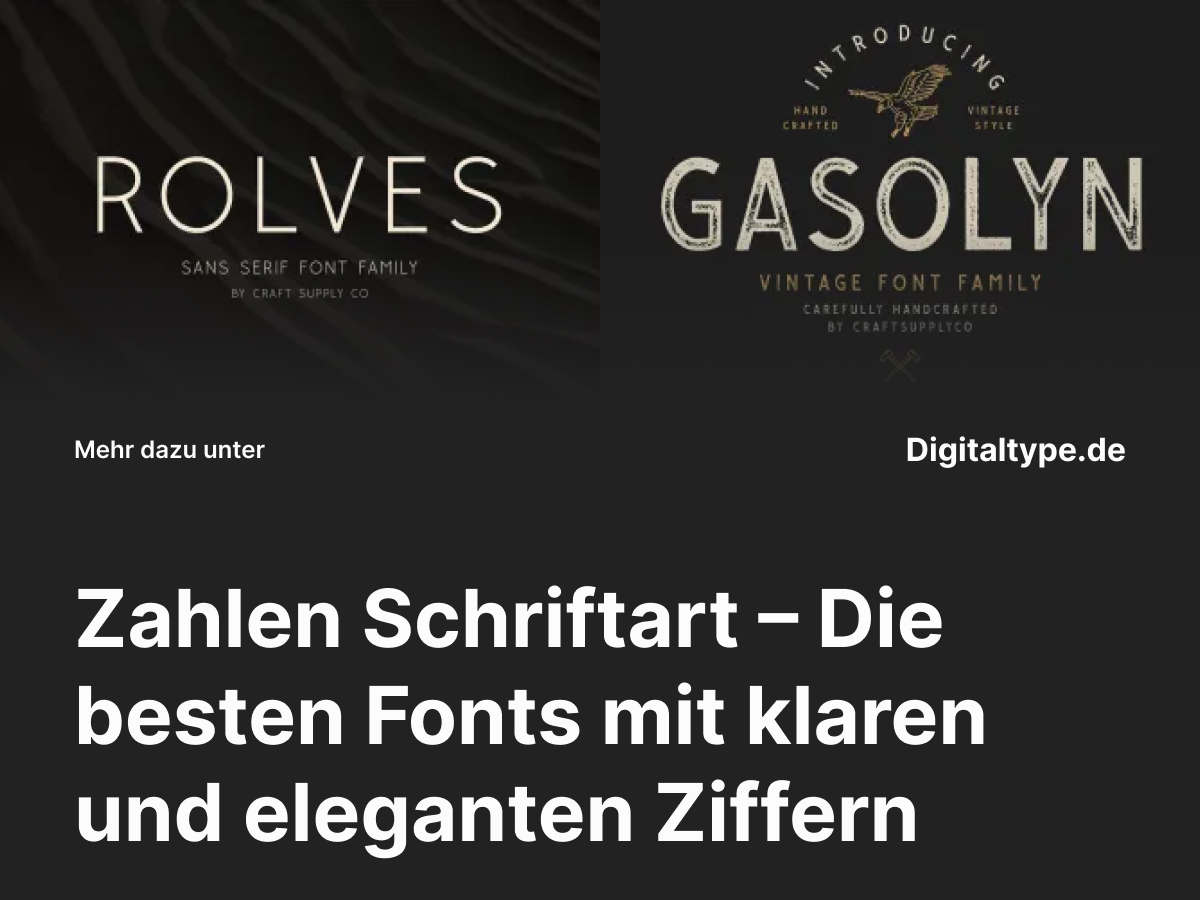
Ob für Preislisten, Infografiken oder Branding – eine gut gestaltete Zahlen Schriftart sorgt für Professionalität und visuelle Harmonie. Zahlen sind ein wesentlicher Bestandteil jedes Designs, und die richtige Schriftart kann sie zu einem echten Hingucker machen.
In diesem Artikel stellen wir dir stilvolle Schriftarten mit präzise gestalteten Ziffern vor, die sich ideal für moderne, elegante und vielseitige Anwendungen eignen.
Was ist eine Zahlen-Schriftart?
Unter einer Zahlen Schriftart versteht man einen Font, bei dem die Ziffern mit besonderem Augenmerk auf Lesbarkeit, Balance und Ästhetik gestaltet wurden. Sie spielt eine wichtige Rolle in Corporate Designs, Magazinen und digitalen Interfaces, wo klare und gleichmäßige Ziffern entscheidend sind.
Eine hochwertige Schriftart mit schönen Zahlen vermittelt Seriosität, Ordnung und Vertrauen – perfekt für Marken, die Wert auf jedes Detail legen.
Designer achten bei Zahlenfonts besonders auf konsistente Linienführung, Proportionen und Rhythmus. So entsteht ein harmonisches Gesamtbild, das Ziffern genauso ansprechend wirken lässt wie Buchstaben.
Wann du eine Zahlen-Schriftart verwenden solltest
- 1. Für Branding und Logos: Wenn dein Markenname oder Slogan Zahlen enthält (z. B. „Studio 89“ oder „Design 24“).
- 2. In Editorials und Magazinen: Für Seitenzahlen, Preisangaben oder Infoboxen mit elegantem Look.
- 3. Für Web- und UI-Designs: Damit Ziffern auf Bildschirmen klar, präzise und professionell wirken.
- 4. In luxuriösen oder technischen Layouts: Ideal für Marken, die Präzision, Qualität und Stil betonen möchten.
Die richtige Zahlen Schriftart sorgt dafür, dass Ziffern nicht nur funktional, sondern auch ästhetisch überzeugen – besonders in Projekten, bei denen Details zählen.
Die 6 besten Zahlen-Schriftarten für moderne Designs
Hier findest du sechs exklusive Zahlen Schriftarten, die durch Klarheit, Eleganz und typografische Qualität überzeugen. Perfekt für Branding, Print, Digital und kreative Designprojekte.
1. Rolves Sans Serif Font Family
Rolves ist eine moderne Sans-Serif-Schrift mit präzisen Ziffern und ausgewogener Geometrie. Ihre klaren Formen eignen sich ideal für Branding, Editorials und digitale Anwendungen, bei denen Lesbarkeit im Vordergrund steht.
2. Gasolyn Font Family + Extras
Gasolyn kombiniert moderne Typografie mit Vintage-Charme. Die Ziffern sind ausdrucksstark und perfekt proportioniert – ideal für kreative Projekte, Plakate und Packaging mit Charakter.
3. Coldiac Luxury Serif Font
Coldiac ist eine luxuriöse Serifenschrift mit fein ausgearbeiteten Zahlenformen. Sie verleiht jedem Design Eleganz und Raffinesse, besonders in Mode-, Schmuck- oder Premium-Branding-Projekten.
4. Riffle Font Family
Riffle bietet moderne Eleganz mit klassischer Struktur. Ihre klaren und gut ausbalancierten Ziffern sind ideal für Geschäftsberichte, Editorials und Corporate Designs, die Seriosität ausstrahlen.
5. Aguero Serif – Clean Elegant Font
Aguero überzeugt durch feine Linien und klare Geometrie. Die Ziffern wirken professionell und elegant zugleich – perfekt für Projekte, bei denen Präzision und Stil im Vordergrund stehen.
6. Espoir Serif Font Family
Espoir ist eine elegante Serifenschrift mit klassischer Note. Ihre sorgfältig gestalteten Ziffern passen perfekt zu edlen Layouts, Magazinen oder Corporate Designs im Premium-Segment.
Design-Tipps für Zahlen-Schriftarten
- 1. Achte auf Lesbarkeit: Besonders bei kleinen Größen oder digitalen Displays sollten Ziffern klar erkennbar bleiben.
- 2. Verwende proportionale Zahlen: Sie sorgen für ein gleichmäßiges Schriftbild im Fließtext.
- 3. Kombiniere Serif und Sans Serif: So entsteht ein dynamischer, moderner Look in deinen Layouts.
- 4. Teste verschiedene Schriftschnitte: Fettere Ziffern können in Überschriften stärker wirken als im Fließtext.
Fazit: Zahlen-Schriftarten für Stil und Präzision
Eine Zahlen Schriftart ist mehr als nur ein funktionales Detail – sie ist ein Ausdruck von Stil, Ordnung und Qualität. Die richtigen Ziffern verleihen deinem Design Eleganz und Professionalität, egal ob digital oder gedruckt.
Die hier vorgestellten Fonts zeigen, wie vielseitig und wirkungsvoll Zahlen in der Typografie eingesetzt werden können. Probiere sie in deinen Projekten aus und verleihe deinen Layouts den letzten Schliff.